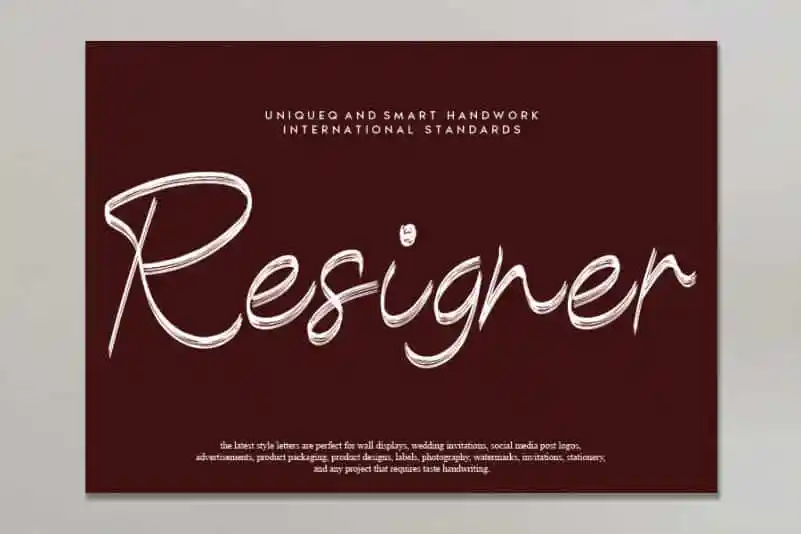
A fonte Resigner Handwritten é uma elegante escolha para qualquer projeto que deseje adicionar um toque autêntico e sofisticado. Masterizada pelo designer andikastudio, ela mantém os influentes traços de calligrafia enquanto se atualiza de maneira contemporânea e inovadora. Ideal tanto para designers gráficos quanto para profissionais de marketing digital, a Resigner é uma fonte que cativa o olhar ao instalar em qualquer projeto. Adotada em elementos visuais diversos, desde títulos até textos decorativos, ela proporciona um equilíbrio perfeito entre a classificação e a originalidade atual. Engane-se se pensar que esta é apenas uma fonte de escrita casual; ela possui o poder para transformar qualquer projeto digital em algo especial e único. Descubra o amor por essa fonte autêntica e leve, e veja como ela pode elevá-lo ao nível superior.